ШРИФТ В КОНТАКТЕ: Как сделать красивый шрифт для Контакта
Сегодня я слегка озадачился поиском подходящего кириллического шрифта, который бы было можно использовать в на картинки. В общем, я решил найти какой-нибудь русский шрифт для фотошопа, и почему-то сразу же вспомнил про красивые надписи, которые используются на большинстве картинок в социальной сети «Вконтакте». Какой шрифт используется ВКонтакте для надписей на картинках? Оказалось для надписей на картинках ВКонтакте чаще всего используют шрифт под названием Lobster (Лобстер).
Если наши варианты оформления Вам не понравились, то Вы легко сможете поменять почерк сами. Так как в стандартных инструментах ВК нет такой возможности, то для того чтобы сделать Ваш статус, или название группы, крутым и необычным необходимо использовать спец. символы языка HTML. Для этого:
Есть два варианта, чтобы сделать Ваш текст прикольным:
- Воспользоваться библиотекой красивых букв на сайте.
- Писать и чередовать текст со специальными символами;
Чтобы реализовать первый способ:
- Выберите понравившийся символ кириллического или латинского алфавита и кликните по нему.
- Нажмите «Копировать».
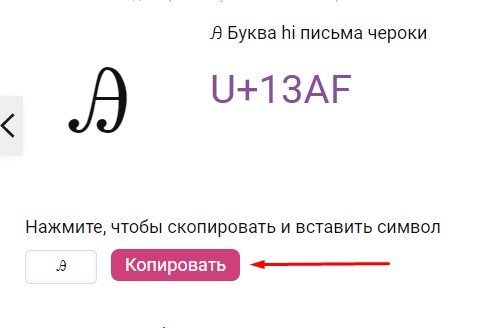
- Вставьте полученную букву в текстовое поле ВК.
- Повторяя данную операцию, Вы можете написать разные слова.
Внимание! Перед публикацией обязательно проверяйте результат на смартфоне. Некоторые символы могут быть размытыми или отображаться неправильно.
Также, чтобы изменить шрифт ,Вы можете чередовать слова или буквы со спец. символами (звездочками, сердечками, смайликами и т.д.) Получить таблицу Вы можете ,например, ЗДЕСЬ. Конечно же, все эти действия удобнее выполнять на компьютере.
Изменить шрифты для Вконтакте автоматически
Чтобы сделать буквы красивыми, Вы можете воспользоваться нашим онлайн генератором. Просто введите свой текст и нажмите на кнопку «Сгенерировать». Для того чтобы поменять стиль оформления, выберите «Изменение стиля». В нашем сервисе Вы можете выбрать 1 из 6 различных вариантов оформления текста. В конце Вам надо просто скопировать понравившийся результат из второй формы и вставить его в свой пост или смс.
Примечание: для изменения почерка повторно нажимайте кнопку «Сгенерировать».
Предупреждение! Первый стиль оформления работает только с кириллическим алфавитом. (UPD 29.07.2021 — латиница добавлена).
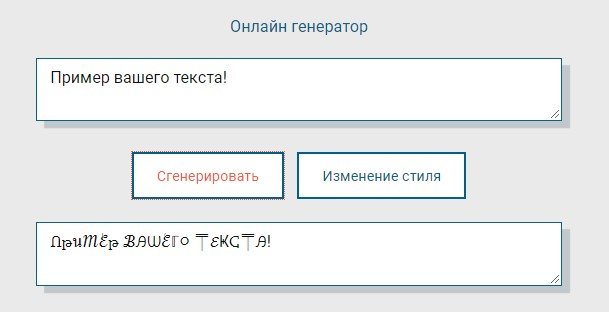
Красивый шрифт для названия группы вк
В заголовке группы так же можно использовать различные возможности для ее украшения. Например можно вставять unicode-смайлики которые привлекут внимание пользователей —